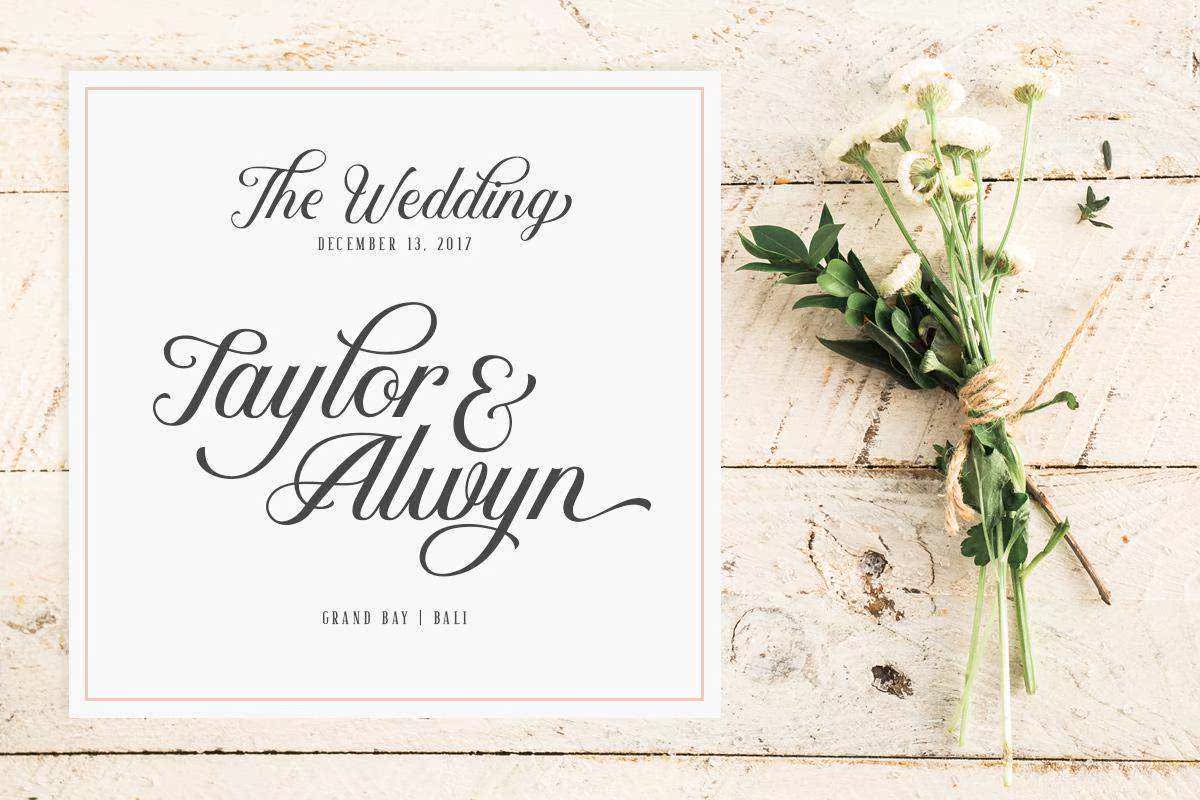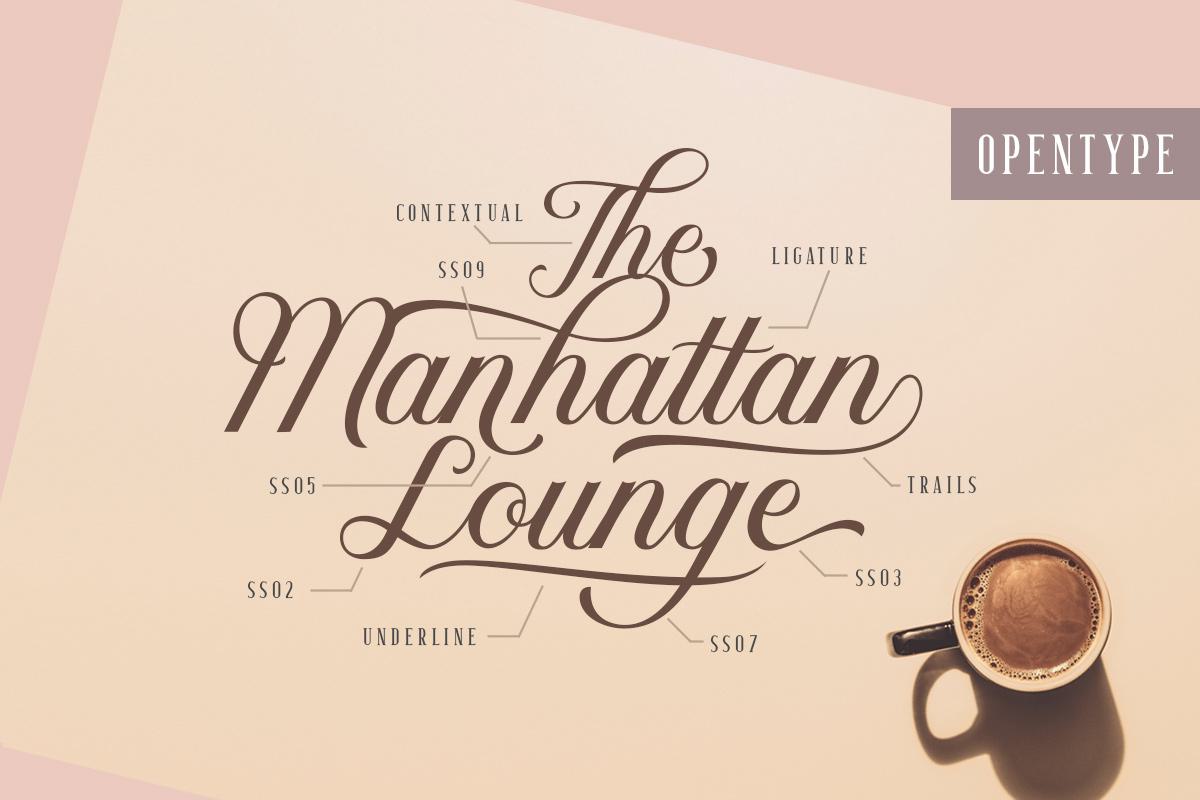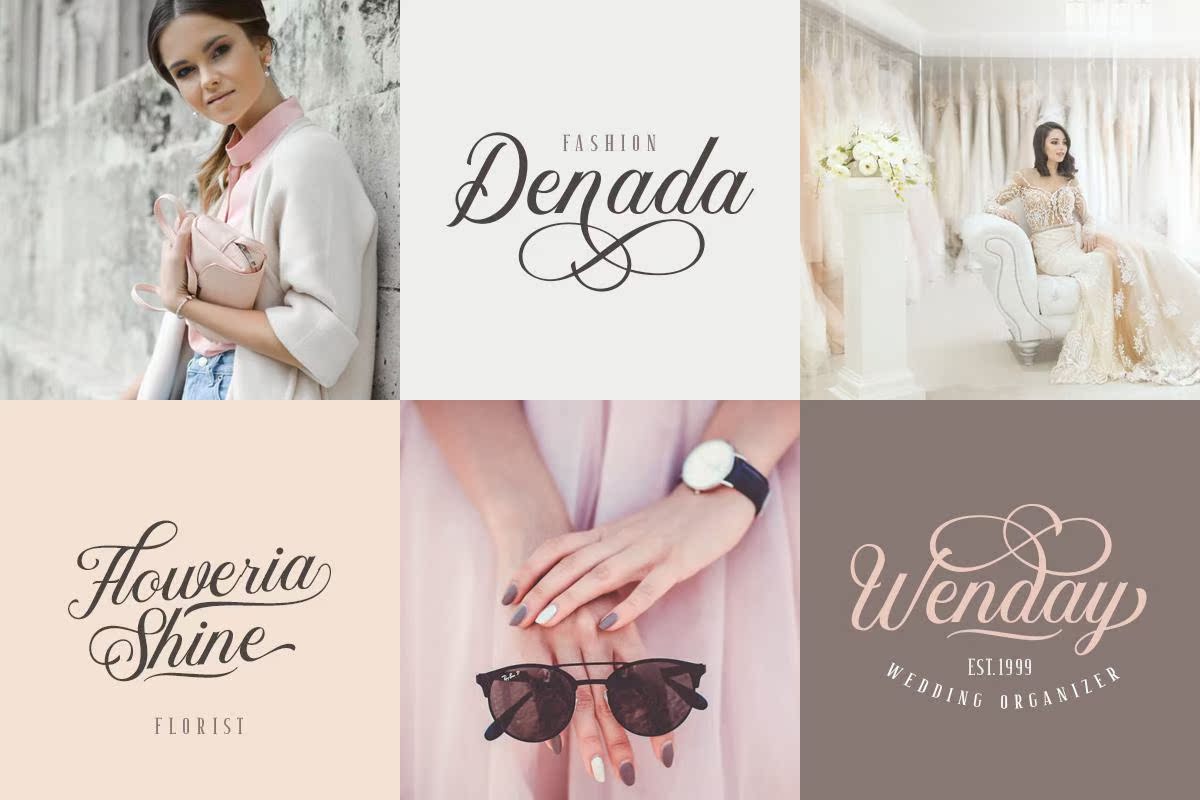
Kaylar是一种由手写体和衬线组成的精美字体。美丽的手写体和衬线完美地匹配,并带来了Galuxury和ClassyFeel。还有什么更专业的是它独特的开放式特征,它几乎可以以简单的方式展示这些装饰。Kaylar是一种由手写体和衬线组成的精美字体。美丽的手写体和衬线完美地匹配Lymatched and Bringaluxury and ClassyFeel。What-Makesite甚至更专业,其独特的开放式功能几乎可以以简单的方式显示这些洗涤装饰。